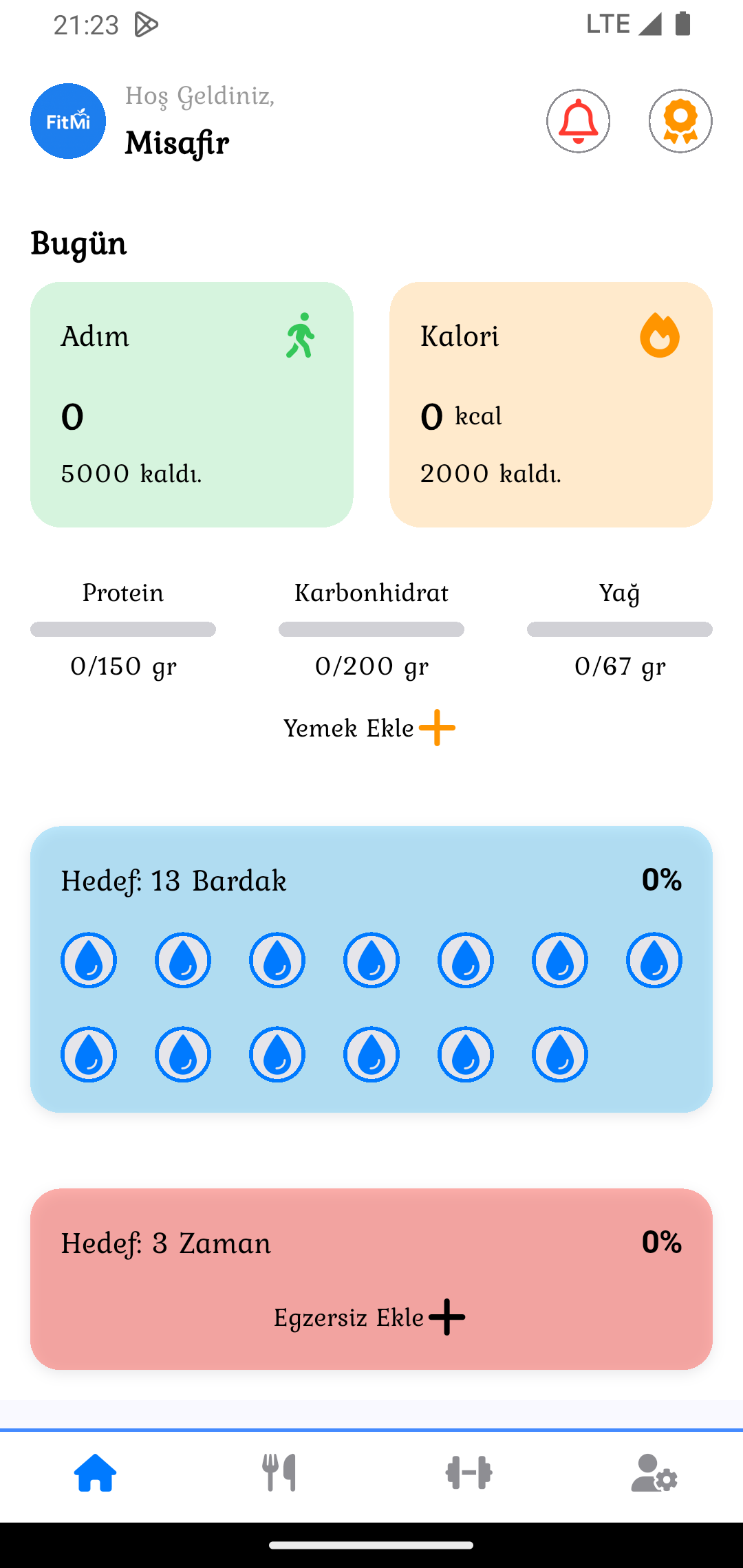
Bu font iyi mi?
- 21-04-2025, 00:29:37İletişim yolu için işlevsel bir font değil, daha düz ve rahat okunabilir fontlara yönelmenizi öneririm.
- 21-04-2025, 00:32:00Arial, Montserrat tarzı domain'ler kullanman senin faydana olur. Bu tarz projelerde fantezi yapmadan, insanların kullanım kolaylığı gözetilerek iş yapılması yeğdir.
- 21-04-2025, 01:17:26Merhaba,
Arial, Helvetica, Roboto, Poppins vb. gibi sık kullanılan ve kullanıcıyı yormayan, sade fontlar kullanılmalı her zaman. Ben mümkün olan işlerde font bile yüklemiyorum sans serif deyip geçiyorum sistem fontu kullanılması için. Hem alışılagelmiş oluyorsun en azından font yapısı olarak, hem de web sitesi özelinde ek sorgu yaratmayarak çok daha optimize bir sonuç almış oluyorsun. Tavsiyem herkese bu yöndedir.